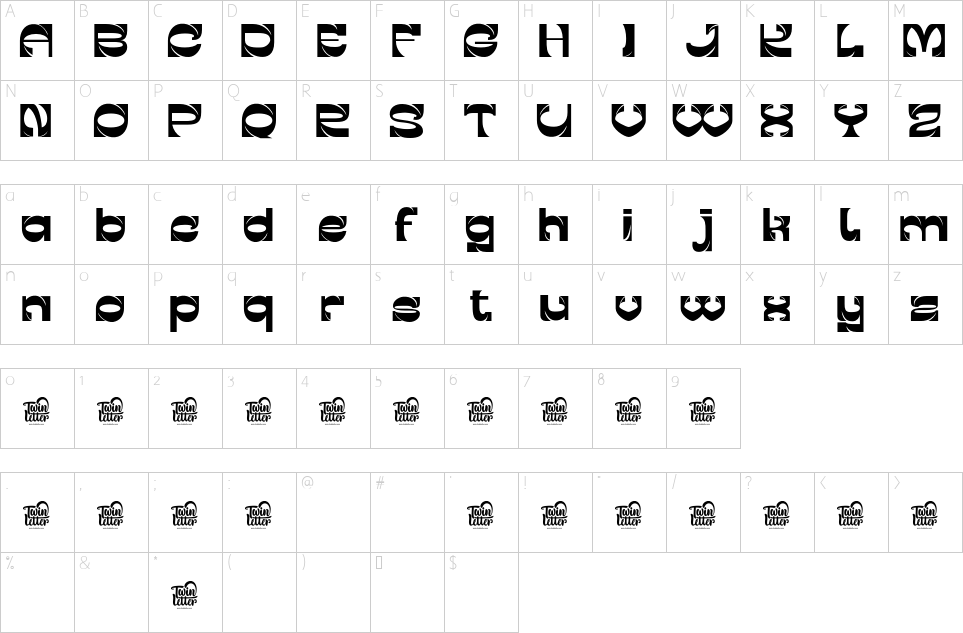
Aqui está uma versão curta e envolvente para a página de download da font Gerakent: Gerakent é uma elegante e moderna fonte que adicionará um toque único ao seu próximo projeto gráfico. Desenvolvida pelo designer rozi, esta font possui um design minimalista que combina perfeitamente com diversos estilos. Com sua interface de 1001 Free Fonts, é simplesmente rápido e fácil baixar a versão para Windows ou Mac. Seja para criar logotipos impressionantes ou adicionar um toque especial ao seu site, Gerakent traz uma variedade de opções de tamanho e estilo que o fará se sentir confortável na hora de aplicar. Com uma design sólido e fluido, a fonte é ideal tanto para uso em impressão quanto para projetos digitais. Se você está procurando por um recurso gráfico versátil com muitas possibilidades, Gerakent será definitivamente uma opção que não pode ser esquecida. Não hesite em experimentar e perceber a diferença que ela pode fazer em seu trabalho.